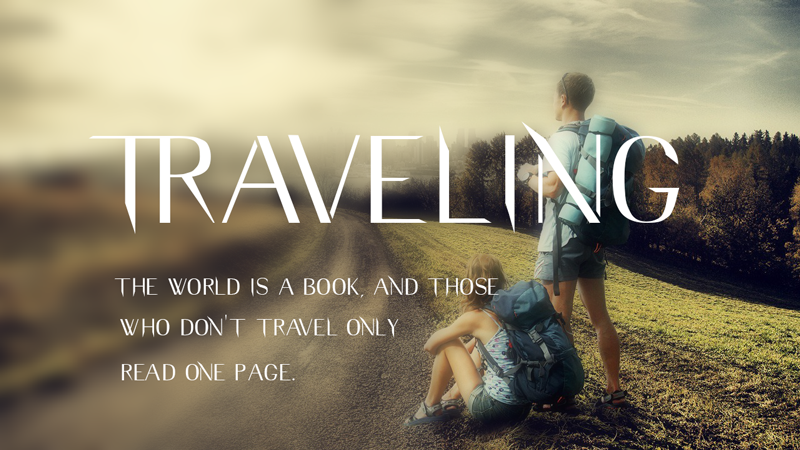
A Traveling Typeface é uma elegante tipografia contemporânea que se inspira em linhas afiadas e limpas. Com seu design simples e limpo, ela oferece a perfeição necessária para diversos ambientes de comunicação, como publicações, títulos, livros, revistas e design corporativo. É perfeitamente adequada tanto para logotipos quanto para marca e embalagens, além de ser ideal para uso em plataformas digitais e televisão. A fonte Traveling é uma escolha perfeita para quem busca um estilo sóbrio que não compromete a simplicidade. Suas linhas finas e bem delineadas criam um contraste harmonioso que se adapta tanto ao texto quanto aos elementos gráficos, oferecendo um toque elegante que torna qualquer projeto de design mais profissional. Seja para criar uma identidade visual única ou aprimorar o seu trabalho em marketing e publicidade, a Traveling Typeface é um elemento imprescindível.